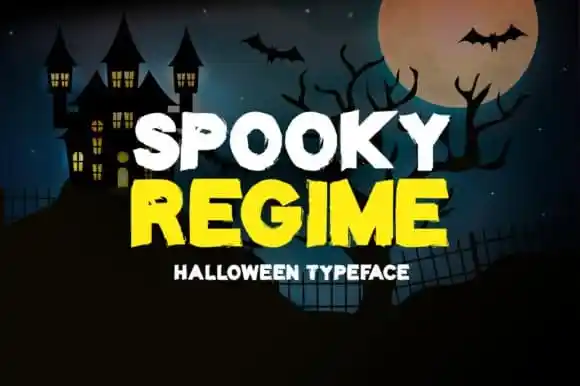
A fonte Spooky Regime Display é inspirada na tinta queimada e dá uma sensação de vibrina de rolo e esfregão seco. Uma excelente adição para qualquer projeto, sua personalização única a torna mais especial ainda. Adicione-a à sua criatividade e veja como ela destaca seus trabalhos! É um tipo multiuso perfeito para anúncios, embalagens, roupas ou design de esportes aventuresco. Através dela, suas ideias ganham vida e são percebidas de uma maneira atraente e inovadora.